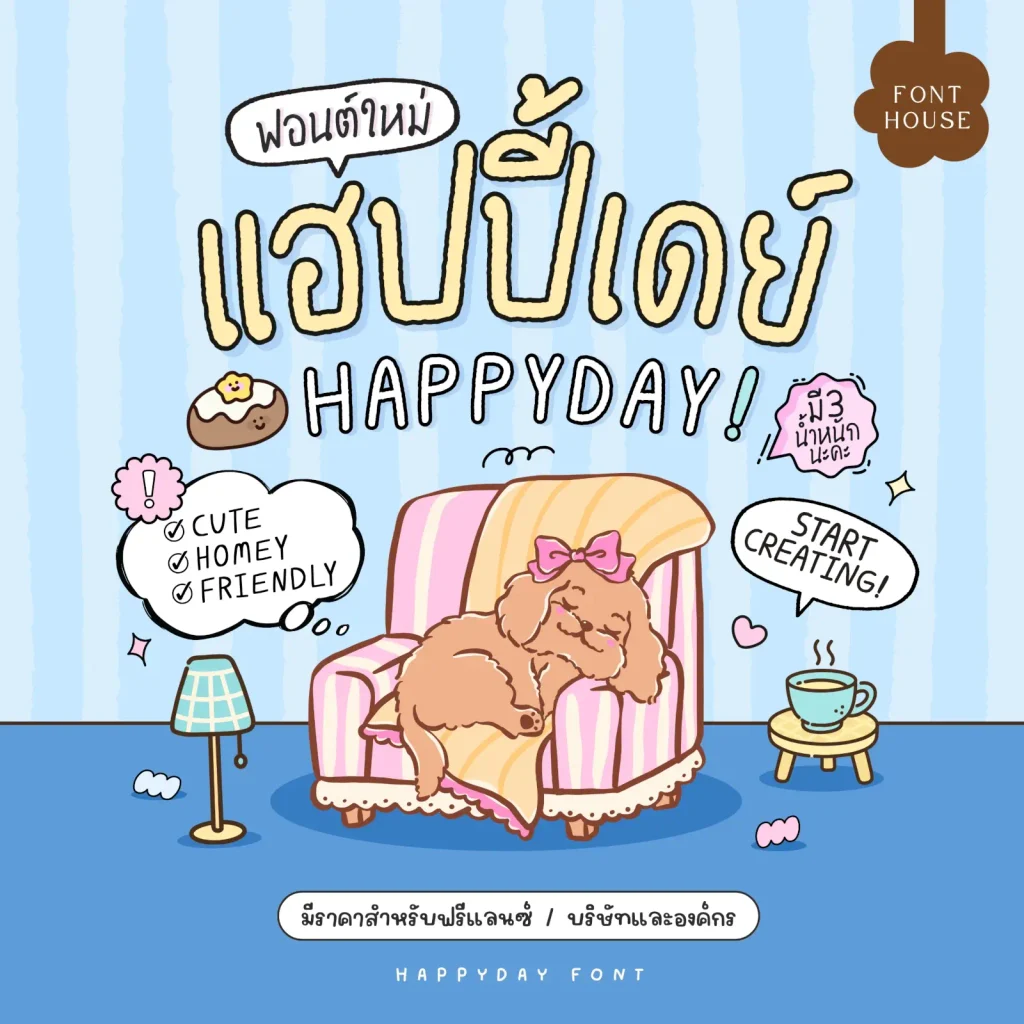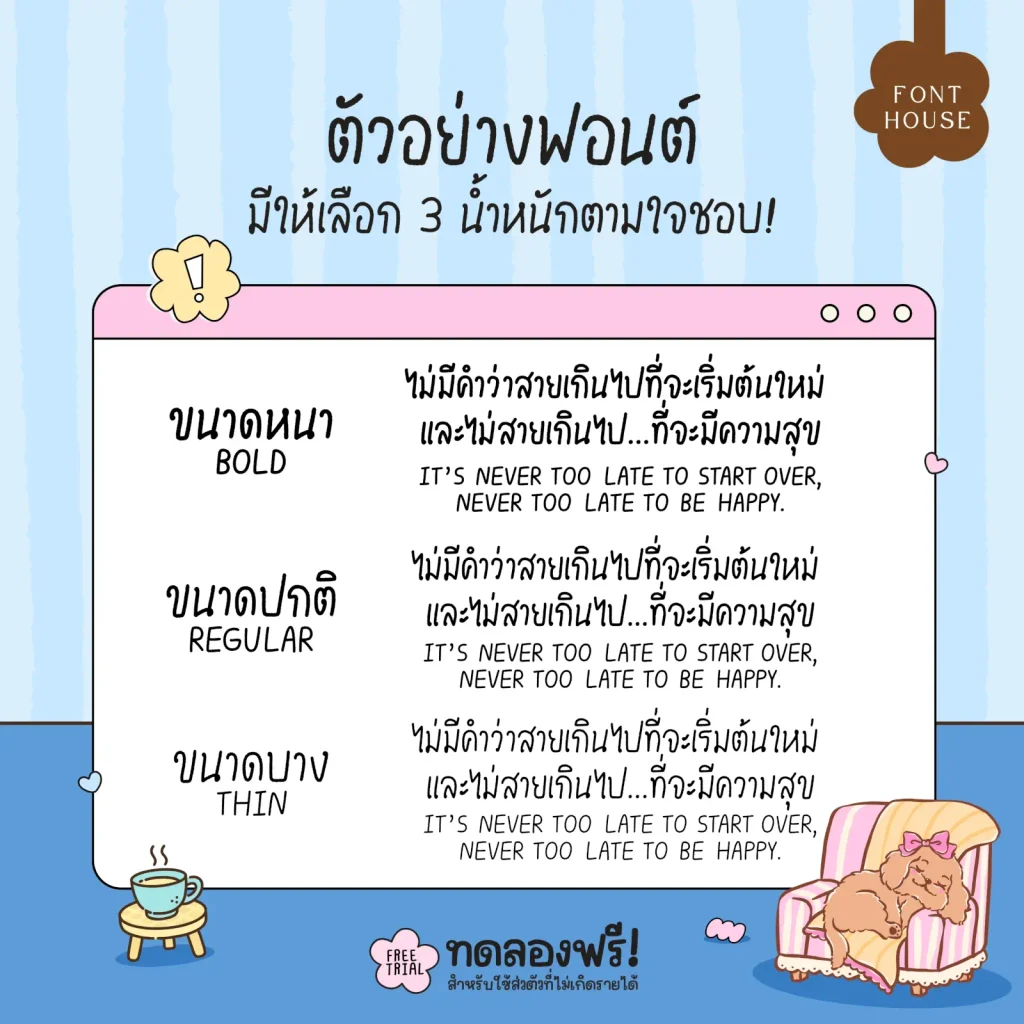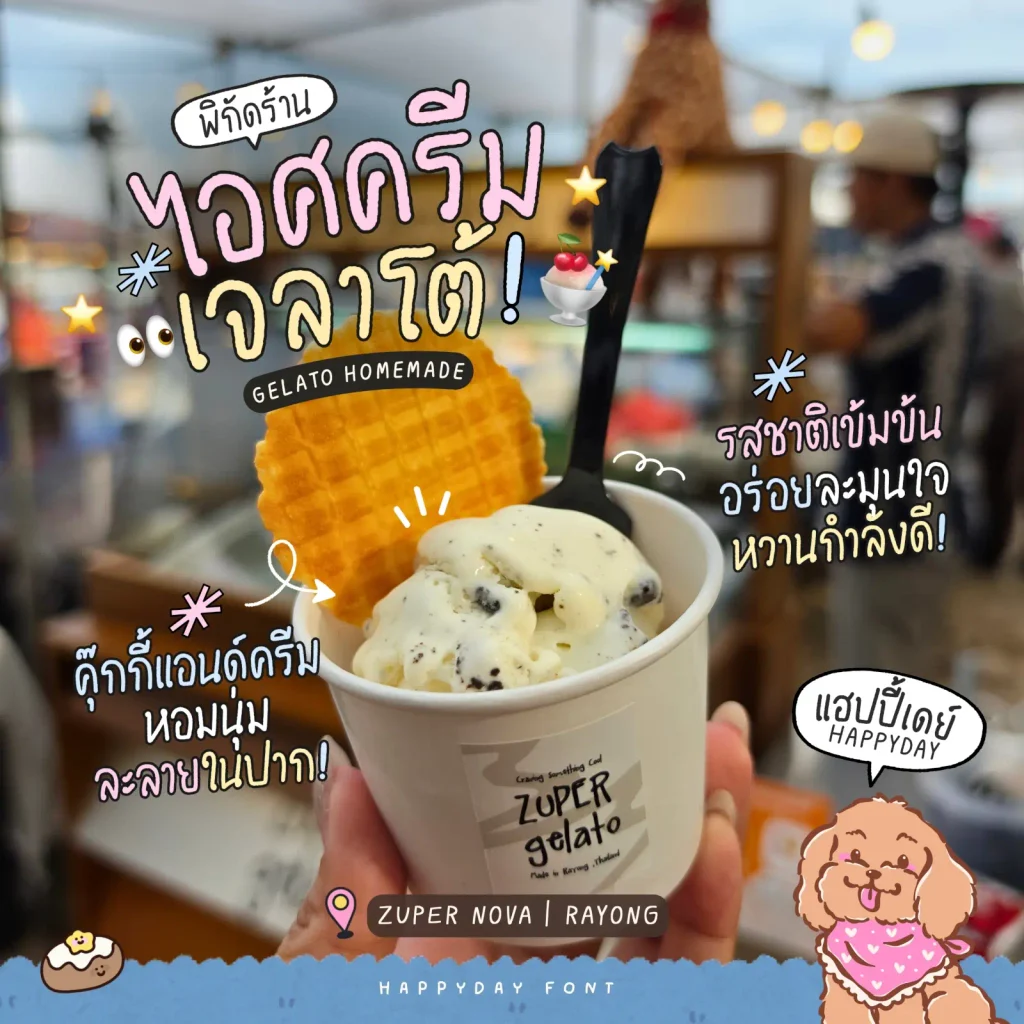
ฟอนต์แฮปปี้เดย์ (FH HappyDay) – ลายมือสไตล์มินิมัล เป็นอีกฟอนต์ลายเส้นที่ได้รับแรงบันดาลใจจากปากกาหมึกซึมและดินสอ ให้ความรู้สึกเหมือนเขียนด้วยมือจริง ถ่ายทอดความอบอุ่น ความจริงใจ ใช้งานง่าย เป็นมิตร อบอุ่น เป็นกันเอง สำหรับงานออกแบบกราฟิก แต่งภาพคอนเทนต์คาเฟ่ หรือโพสต์รีวิวก็ดูน่าสนใจ
- มี 3 น้ำหนัก
แฮปปี้เดย์ (FH HappyDay)